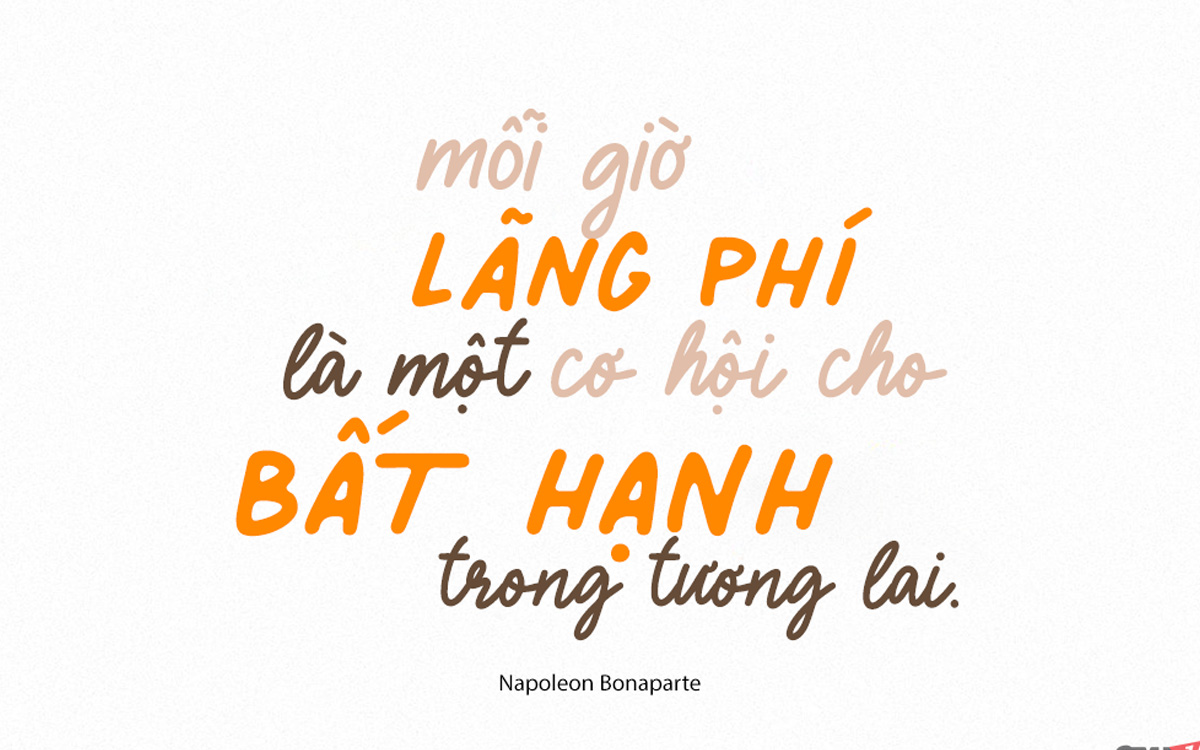
[Tải xuống] 19+ Font chữ cute Việt hóa bạn không thể bỏ qua trong thiết kế
Trong lĩnh vực thiết kế đồ họa, font chữ đóng vai trò vô cùng quan trọng trong việc truyền tải cảm xúc, phong cách và thông điệp của một dự án. Đối với những dự án mang tính chất dễ thương, đáng yêu, việc chọn lựa font chữ cute là yếu tố then chốt giúp tạo ra ấn tượng ban đầu mạnh mẽ. Để hỗ trợ bạn trong việc lựa chọn những font chữ phù hợp, dưới đây là danh sách hơn 19 font chữ cute miễn phí mà bạn không thể bỏ qua cho thiết kế của mình.
Lợi ích của việc sử dụng font chữ cute trong thiết kế
Font chữ cute không chỉ giúp dự án của bạn trở nên bắt mắt mà còn mang lại nhiều lợi ích trong quá trình thiết kế, bao gồm:
• Truyền tải phong cách dễ thương: Các font chữ cute thường có đường nét mềm mại, tròn trịa, phù hợp với những dự án cần thể hiện sự dễ thương và thân thiện, chẳng hạn như thiết kế cho trẻ em, thú cưng, hay các sản phẩm handmade.
• Tạo điểm nhấn cho dự án: Khi sử dụng đúng cách, font chữ cute có thể trở thành yếu tố trọng tâm, thu hút sự chú ý và giúp nổi bật thông điệp.
• Tăng tính cá nhân hóa: Những font chữ dễ thương mang lại cảm giác gần gũi, thân thiện, dễ tiếp cận với người xem.
Danh sách 19+ font chữ cute miễn phí
Dưới đây là hơn 19 font chữ cute miễn phí từ nhà S99.vn mà bạn có thể dễ dàng tải về và sử dụng cho các dự án của mình:
Font chữ vui vẻ dễ thương SVN Claytonia
SVN Claytonia là font chữ vui nhộn, đáng yêu, được thiết kế dành riêng cho các dự án liên quan đến trẻ em hoặc đồ ăn. Font này có nét tròn mềm mại và các chi tiết hoạt hình, tạo cảm giác vui tươi và năng động. Font phù hợp cho các thiết kế đồ họa, nhãn dán, và poster quảng cáo.
Font Monday Feelings Việt hóa - Cute và hoạt hình
Font Monday Feelings mang đến cảm giác vui tươi và ngộ nghĩnh, với các đường nét đáng yêu phù hợp cho các thiết kế đồ họa trẻ em, sản phẩm quảng cáo đồ ăn hoặc đồ dùng học tập. Các ký tự được thiết kế tỉ mỉ, tạo cảm giác sinh động và thu hút người xem.
Font chữ cute béo tròn SVN Ziclets Việt hóa
SVN Ziclets là một font chữ hoạt hình dễ thương, béo tròn với phong cách vui vẻ và nhí nhảnh. Các ký tự được thiết kế tròn trịa, tinh nghịch, tạo cảm giác gần gũi, thích hợp cho các thiết kế poster quảng cáo, banner, hoặc sản phẩm đồ ăn nhanh. Đặc biệt, font này rất phù hợp với các dự án cần sự sinh động, vui tươi và hướng tới đối tượng trẻ em.
Phông chữ Bagel Fat One dễ thương Việt hóa
Font Bagel Fat One nổi bật với nét chữ béo tròn, tạo cảm giác dễ thương và thân thiện. Đây là font chữ lý tưởng cho các thiết kế logo, nhãn mác, hoặc đồ dùng cho trẻ em. Các nét vẽ tròn mập của font mang lại sự thu hút và vui tươi cho mọi thiết kế.
Font TH Mighty Kingdom đáng yêu Việt hóa
TH Mighty Kingdom là một font chữ hoạt hình cute, vui vẻ, với nét vẽ tròn trịa và đáng yêu. Các chữ cái được thiết kế ngộ nghĩnh, tạo nên sự thân thiện và phù hợp cho các dự án thiết kế đồ họa liên quan đến trẻ em hoặc đồ ăn.
Font chữ béo tròn cute TH Yorkmade Việt hóa
Font TH Yorkmade là một font chữ viết hoa béo tròn, mang lại cảm giác dễ thương và tinh nghịch. Các ký tự tròn trịa và mềm mại của font này giúp nó phù hợp với các thiết kế trẻ em, đồ họa hoạt hình, hoặc logo dành cho các thương hiệu đồ ăn. Với phong cách đáng yêu, font này rất lý tưởng để tạo điểm nhấn cho các tiêu đề và banner.
Font TH Christ Moon Việt hóa chủ đề giáng sinh
TH Christ Moon là font chữ hoạt hình dễ thương, mang phong cách nhẹ nhàng và tinh nghịch, rất phù hợp cho các dự án thiết kế liên quan đến trẻ em hoặc đồ ăn. Với các nét vẽ tròn trịa và đáng yêu, font này mang đến cảm giác ấm áp và gần gũi. TH Christ Moon sẽ là lựa chọn hoàn hảo cho thiết kế bao bì, banner hoặc sản phẩm quảng cáo đòi hỏi sự dễ thương và nổi bật.
Font TH Cupid Darling Việt hóa dễ thương
Font TH Cupid Darling là một font chữ hoạt hình vui vẻ và đáng yêu, phù hợp cho các thiết kế đồ họa liên quan đến trẻ em hoặc quảng cáo đồ ăn. Với nét vẽ mềm mại và chi tiết tinh tế, font này mang lại cảm giác dễ thương và thân thiện.
Phông chữ SVN Carrotflower cute Việt hóa
SVN Carrotflower là một font chữ hoạt hình vui nhộn và sinh động, phù hợp cho các thiết kế liên quan đến trẻ em hoặc sản phẩm đồ ăn. Font này có các nét chữ mềm mại và đáng yêu, tạo cảm giác vui vẻ và năng động.
Font chữ SVN Clouds Caprice đáng yêu
SVN Clouds Caprice là font chữ hoạt hình dễ thương với các nét chữ tròn trịa, mang lại cảm giác nhẹ nhàng và vui vẻ. Font này lý tưởng cho các thiết kế logo, banner hoặc các sản phẩm quảng cáo liên quan đến trẻ em.
Kết luận
Font chữ cute là một yếu tố quan trọng giúp các dự án thiết kế trở nên thu hút và ấn tượng hơn. Với danh sách 19+ font chữ cute miễn phí được S99.vn giới thiệu ở trên, bạn có thể dễ dàng lựa chọn cho mình những font phù hợp nhất để tạo nên những tác phẩm độc đáo và sáng tạo. Hãy nhớ rằng, việc sử dụng font chữ cute không chỉ giúp truyền tải cảm xúc mà còn tạo ra dấu ấn riêng cho dự án của bạn.